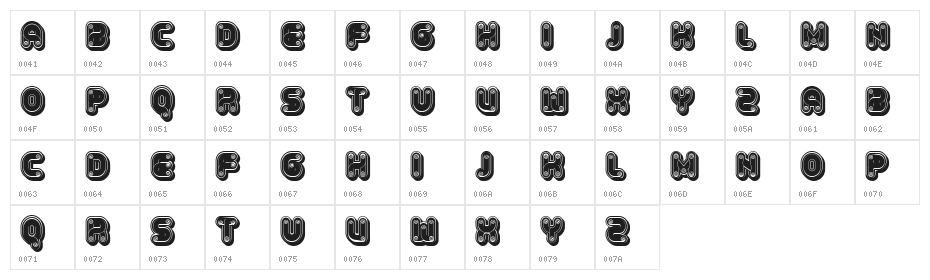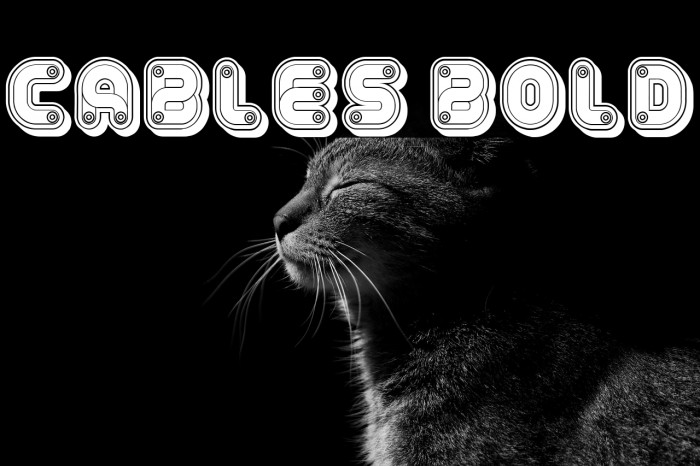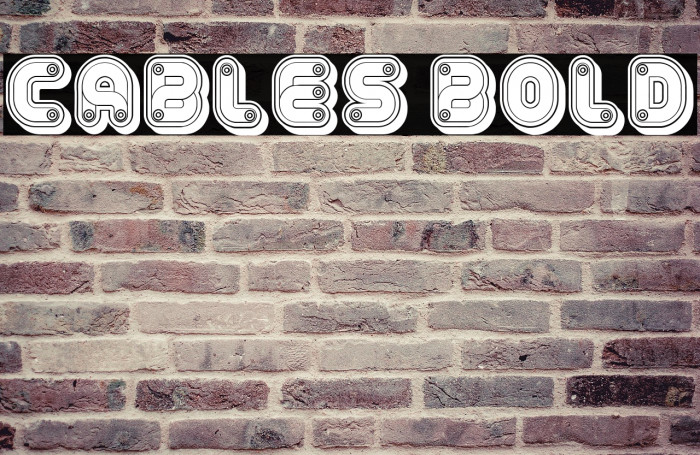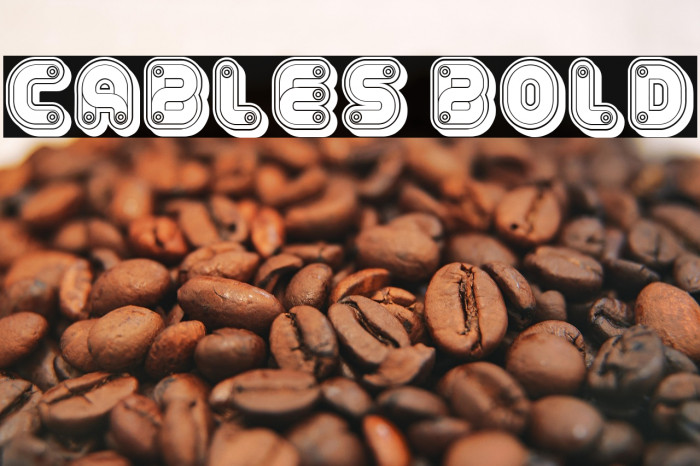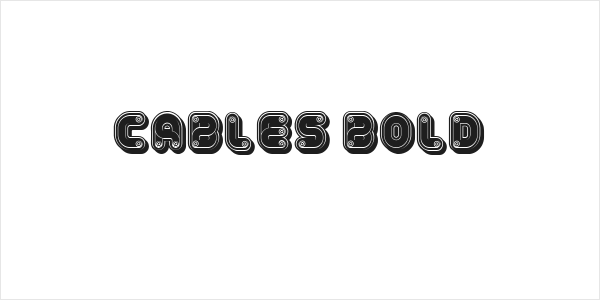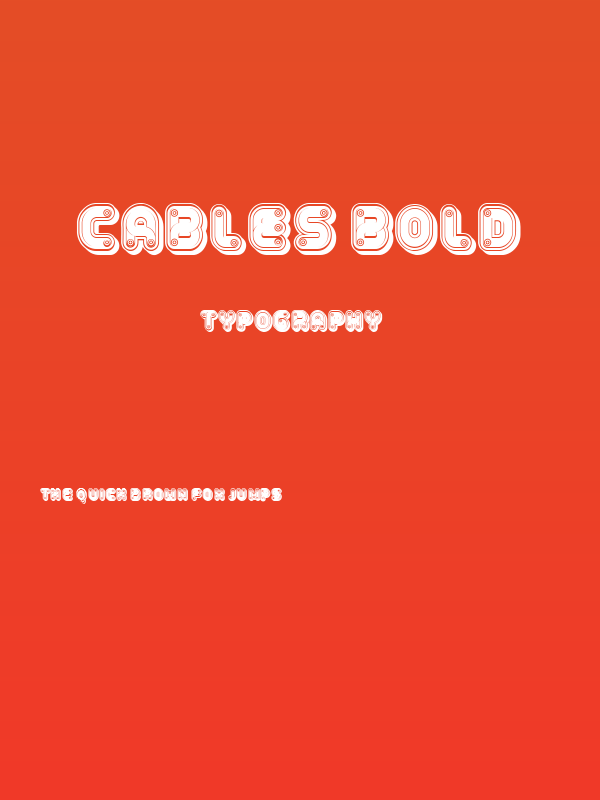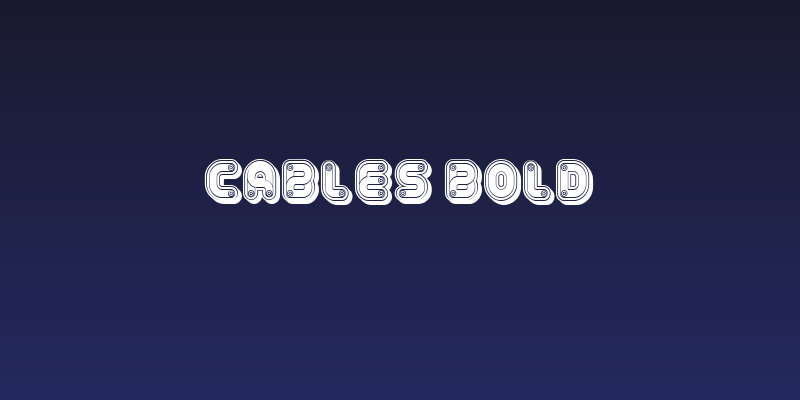
Cables Bold Font
| Projets proposés | Ideal for technology branding, futuristic posters, video game titles, and any project needing a modern, industrial look. |